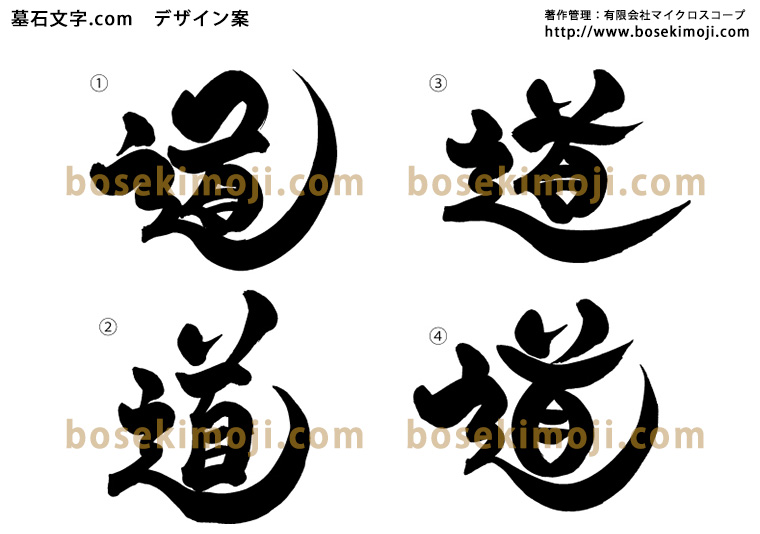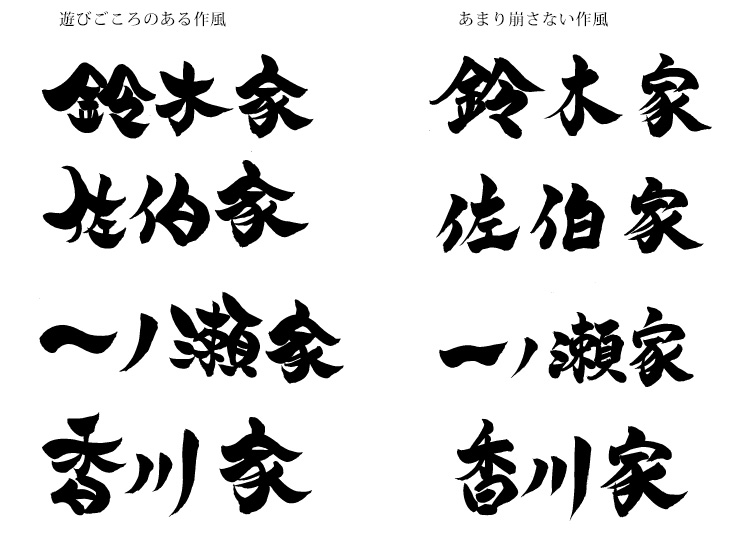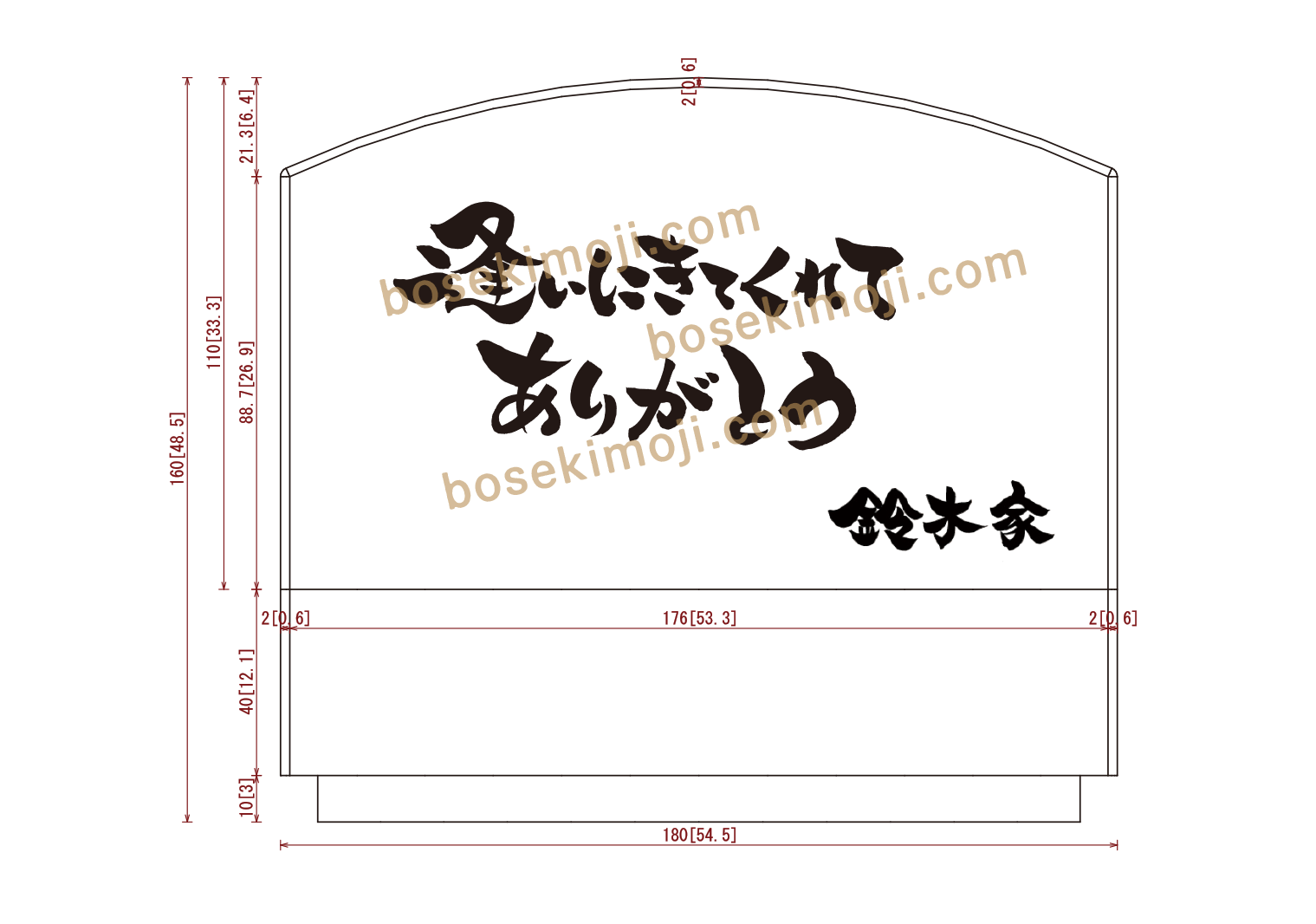
墓石に刻む文字を自由に。ご希望の言葉や家名を書にいたします。
言葉に込めた想いや書体のイメージなど、ご希望に沿えるよう3点書き下ろし、お選びいただきます。修正は無料です。
ご依頼内容:仕事仕事で人生を駆け抜けたようなお父様。依頼主様は、事あるごとにお父様に頼って相談されていました。これからも家族の道しるべ・羅針盤でいてくださいという想いから「道」という字に決められたそうです。
①太さと柔らかさの中に動きのあるイメージ
②凛としたイメージ
③伸び伸びとしたイメージ
④自由さに柔らかさを加えて
左:遊び心のある作風
右:あまり崩さない作風